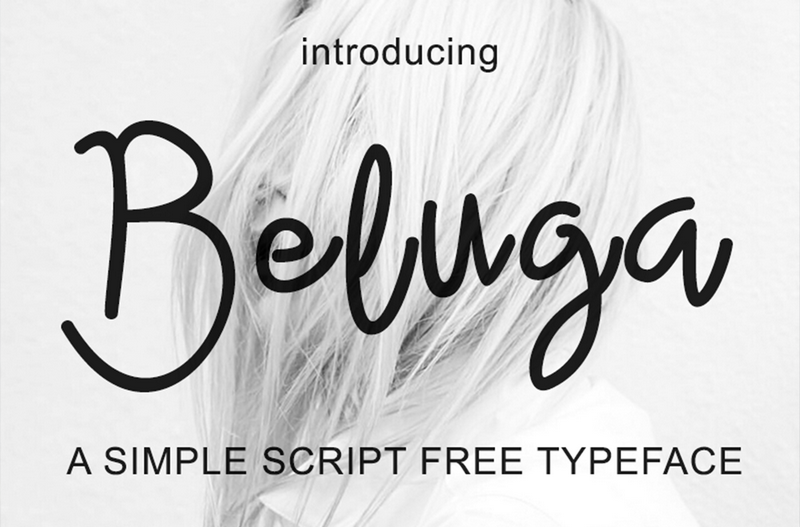
Beluga Script é uma fonte tipográfica script, criada com um toque de letra realista, que traz 390 guílos para os designers e fãs do estilo alegre. Criada pelo designer Polythene Designs, esta font oferece um caráter romântico e mágico que é perfeito para projetos variados como logotipos, anúncios, mensagens pessoais ou em embalagens. Beluga Script é uma escolha inteligente para aqueles que buscam uma fonte com ares de romance e leveza na sua próxima peça visual. Com seu design elegante, a fonte atua perfeitamente como o elo final para projetos onde a escrita à mão tem um lugar especial.